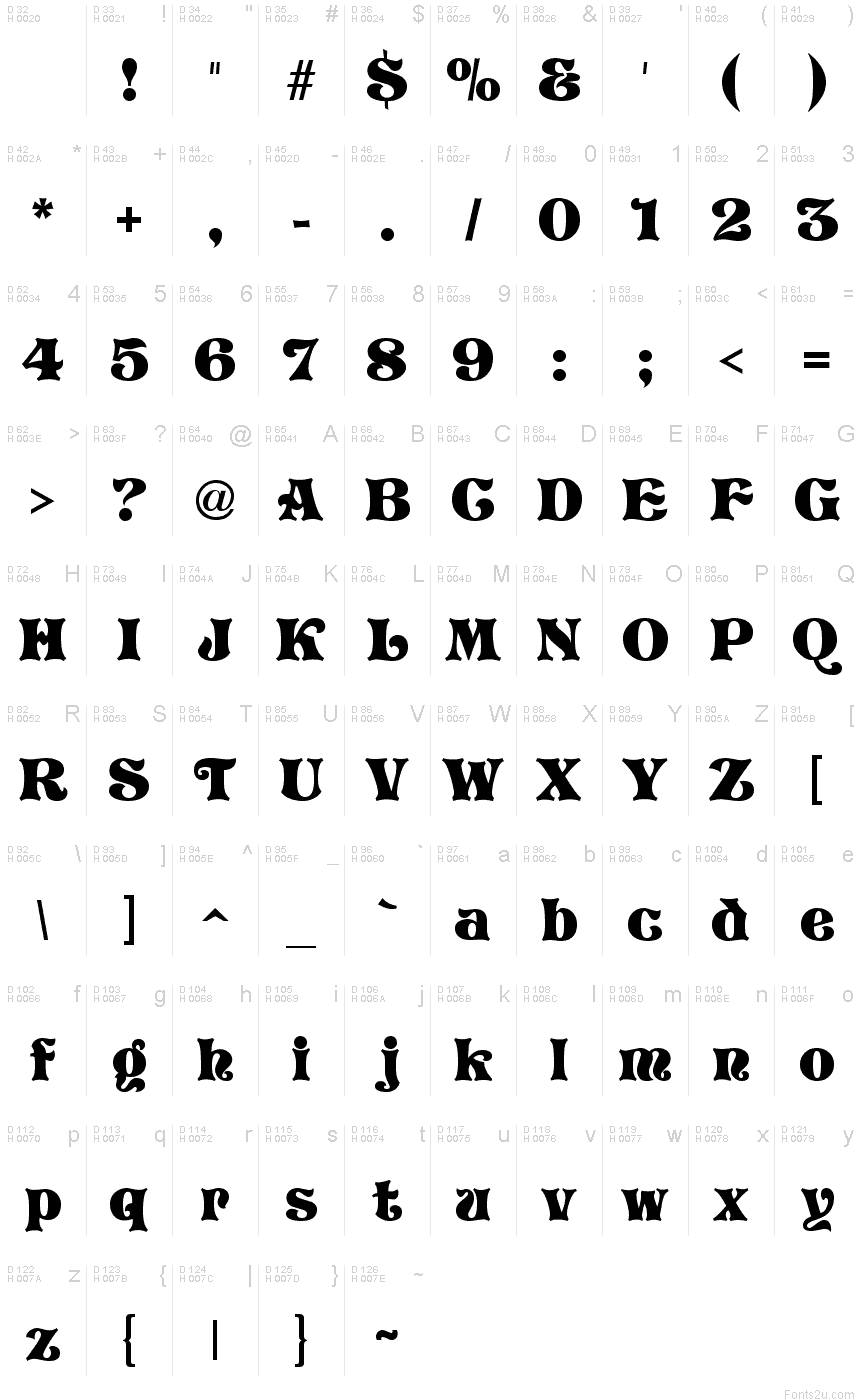
Vostrey
Vostrey to darmowy, retro-średniowieczny font typu display z miękkim, wyrazistym charakterem. Litery łączą w sobie echa blackletteru z fantazyjnymi krzywiznami lat 70. – szerokie, rozszerzane szczyty, ciężkie, zaokrąglone formy i kilka ostrych, skierowanych do wewnątrz cięć, które nadają stylowi teatralnego, a nie staroświeckiego wyrazu.
Naturalnie pasuje do okładek książek, brandingu karczm, plakatów festiwalowych, tytułów gier i nastrojowych opakowań, gdzie ten darmowy font wnosi ludowy, bajkowy klimat. Wykorzystaj go w krótkich nagłówkach, nazwach i logotypach, ponieważ te masywne krzywizny i rogate szeryfy najlepiej sprawdzają się w krótkich tekstach.